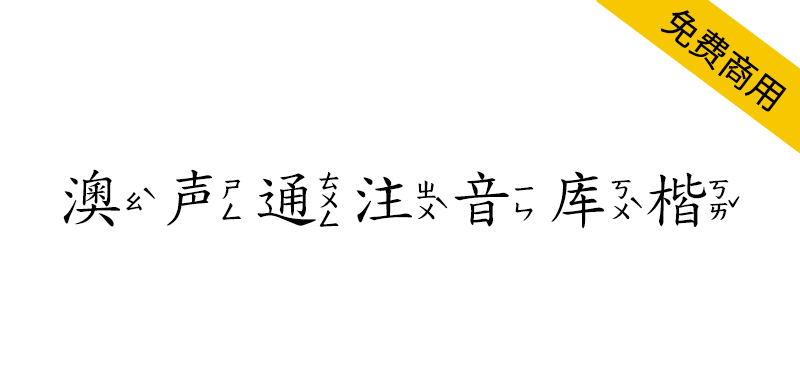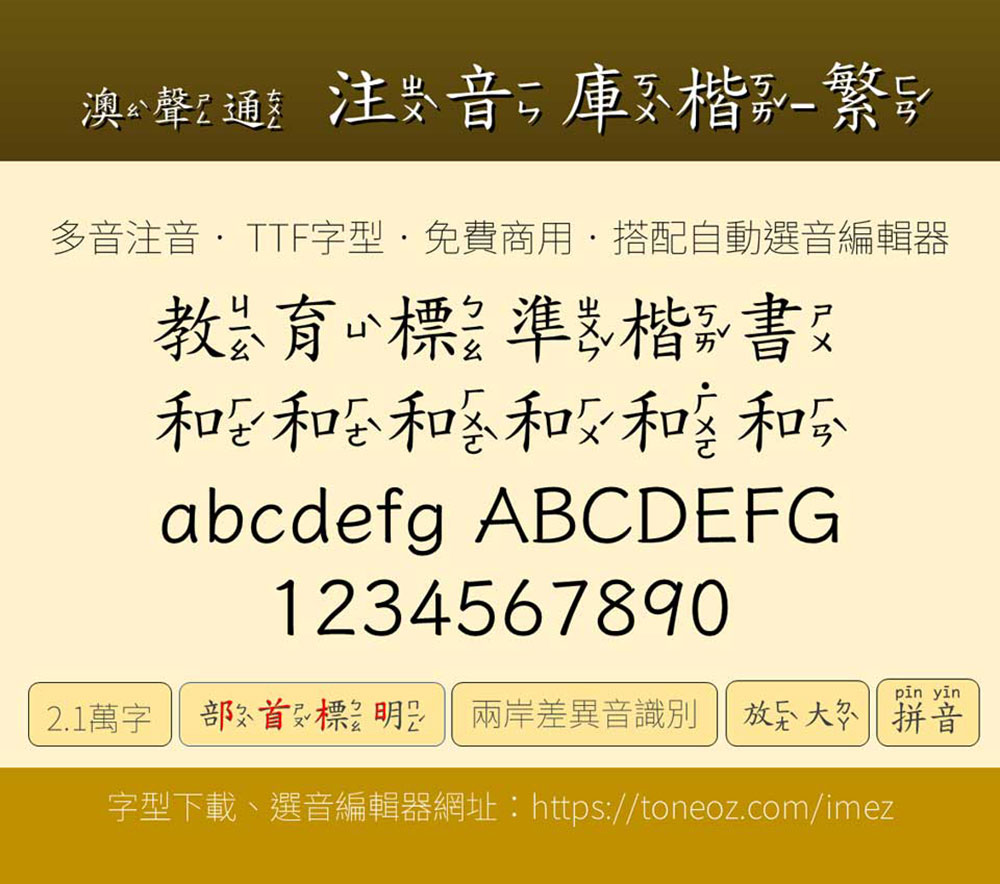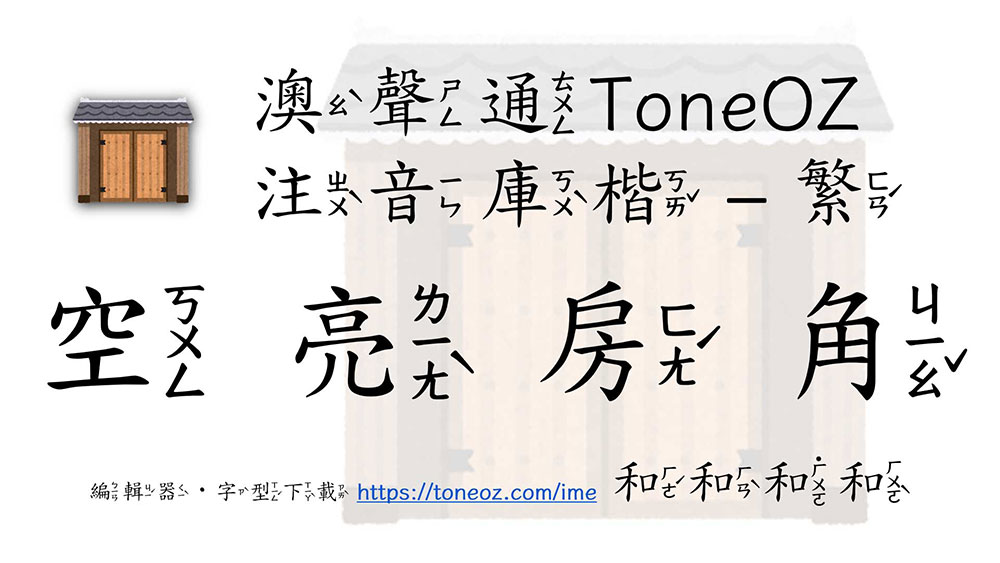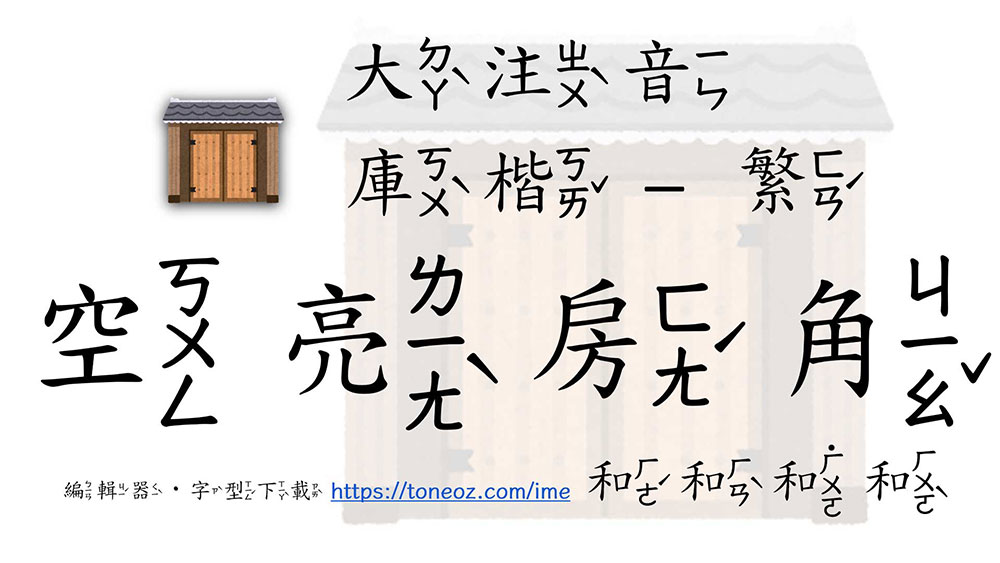
澳声通注音库楷是一款基于全字库正楷体的标准楷体台湾注释音字型,免费商用,满足中文现场教学需求
注意:大注音版的注音很大,适合标题,注音部分可能会与邻近字重叠,使用时请斟酌搭配字距行距或加上空白使用。
原始楷体字型来自两岸中文教学时常用的全字库正楷体,并根据《开放政府数据许可证,版本 1.0》授权许可:
拼音和非汉字字形基于FONTWORKS的Klee One,根据 SIL Open Font License 1.1(SIL 开源字型授权版本1.1,简称SIL OFL 或OFL)授权协议发布:
注音字形基于 But Ko 所著的《GenyoMinBopomofo-Regular》,根据 Apache 2.0 许可使用,这个授权的自由度非常高: